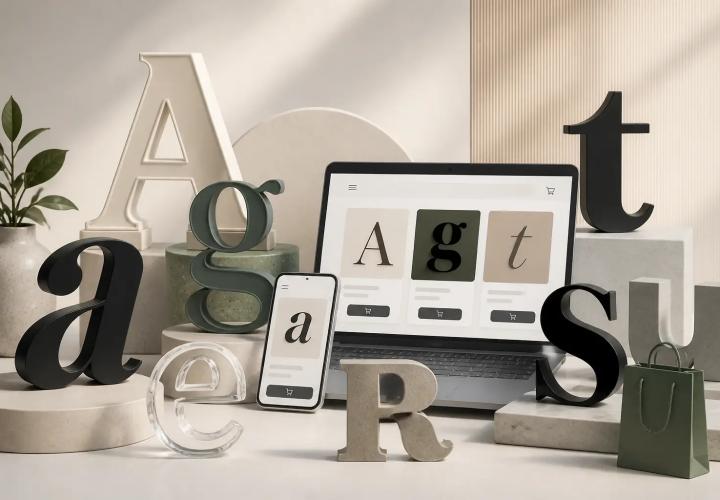
Beliebte Typografie im Onlinehandel
Eine aktuelle Auswertung von Sufio, basierend auf Daten von über zwei Millionen Shopify-Shops, zeigt welche Schriftarten im modernen E-Commerce am häufigsten zum Einsatz kommen. Die Ergebnisse geben interessante Einblicke in Lesbarkeit, Markenwirkung und Konversion. Im Fokus stehen dabei klare serifenlose Schriften, die auf Bildschirmen aller Größen gut funktionieren, sowie gezielte Akzentsetzungen durch Fette oder kondensierte Breiten.
Unter den beliebtesten Fonts finden sich Klassiker wie Sans-Serif-Familien, die durch gute Lesbarkeit überzeugen. Aber auch gezielter Einsatz von Serif-Schriften kann Markenpersönlichkeit erzeugen, besonders in Kopfzeilen oder Produktbeschreibungen, die Vertrauen und Tradition vermitteln sollen. Der Trick liegt oft in der Balance: Haupttext bleibt gut lesbar, Überschriften erhalten Charakter durch eine kontrastreiche Typografie.
Was bedeutet das für Designer und Shop-Betreiber?
Für Webdesign und UX ist die Wahl der Schrift nicht nur ästhetisch, sondern funktional. Leseabstände, Schriftgröße, Zeilenhöhe und Zeilenlänge beeinflussen, wie lange Besucher auf einer Seite verweilen und ob sie eine Handlung ausführen. Die Studie zeigt außerdem, dass konsistente Typografie Markenwucht erzeugt: Gleichbleibende Schriftarten über alle Kanäle hinweg stärken Wiedererkennung und Vertrauen bei der Kundschaft.
Besonders relevant ist die technische Seite: Viele Shops setzen heute auf Webfonts, die trotz größerer Dateigröße schnelle Ladezeiten liefern müssen. Hier empfiehlt sich eine kluge Subsetierung, Komprimierung und die Nutzung moderner Formate wie WOFF2. Wer sich unsicher ist, findet in der Praxis oft den Mittelweg: Eine Hauptschrift für Fließtext, dazu eine charakterstarke Display-Schrift für Headlines und Call-to-Action-Elemente. Darauf aufbauend lässt sich ein flexibles Typografie-System etablieren, das sich über verschiedene Devices gut anpasst.
Für Shop-Betreiber lohnt sich ein Audit der bestehenden Typografie: Welche Schrift wird in Produktseiten, Kategorieseiten und Checkout-Prozessen verwendet? Wie wirkt sie im Zusammenspiel mit Bildern und Farbschemata? In vielen Fällen genügt eine kleine Anpassung, um die Lesbarkeit zu erhöhen und Konversionen zu steigern. Wer Unterstützung braucht, kann sich an spezialisierte Agenturen wenden: 4eck Media begleitet Unternehmen bei Webdesign, SEO und schnellen Webseiten, idealerweise mit konsistenter Typografie als Basis.
Ausblick und Praxis-Tipps
- Setze eine klare Hauptschrift für Fließtext, z. B. eine moderne Sans-Serif, die gut lesbar ist.
- Wähle eine Display-Schrift für Headlines, die Markencharakter verleiht, aber mit der Hauptschrift harmoniert.
- Achte auf konsistente Typografie über alle Seiten hinweg und teste Reaktionsfähigkeit auf Mobilgeräten.